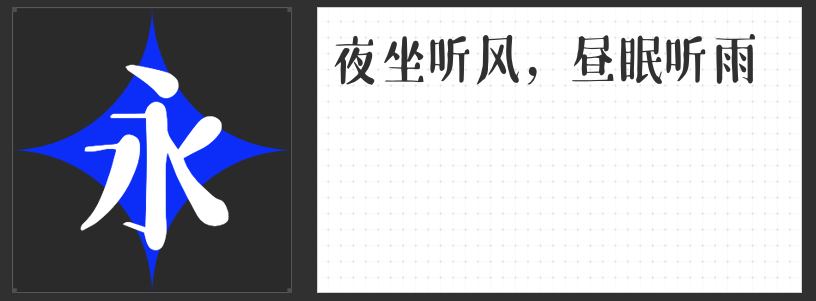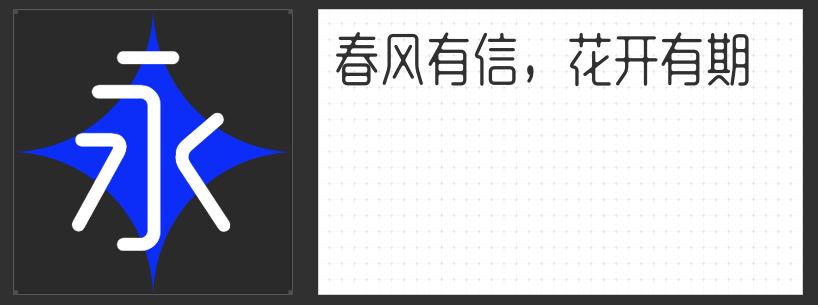
四款创意字体赋能包装设计:让视觉语言焕发独特魅力
在竞争激烈的包装设计领域,字体的选择往往成为品牌传递个性与情感的关键载体。一款兼具创意与实用性的字体,不仅能提升产品辨识度,更能通过视觉语言与消费者建立情感共鸣。以下四款非免费创意字体,以其独特的设计语言与美学表达,为包装设计注入鲜活生命力。
一、高手庆科自由宋 常规
这款以手写感为基底的宋体,突破传统宋体的刻板印象,通过圆润略瘦长的字形与适中的中宫设计,营造出灵动而不失雅致的视觉效果。横画末端的圆形装饰角与细长圆润的钩笔,赋予文字趣味性;西文符号的圆润处理更与中文形成风格统一,适用于追求文化底蕴与年轻化表达的品牌包装。
二、字恋狂风摇简 粗体
“摇晃感”是这款字体的核心标签。通过失衡的笔画比例与歪扭的线条,模拟被风吹拂的动态,传递出温暖而随性的视觉温度。其手写特质与夸张的形态处理,适合用于儿童产品、手作工艺或强调人文关怀的包装设计,以不规则的美感打破常规,激发情感共鸣。
三、励字志向黑简 中粗
圆体与黑体的融合创新,赋予这款字体独特的视觉张力。外圆角的笔画拐角设计,在保持字形稳重的同时注入灵动气息;充实的字面与稳定的结构适配屏显需求,使其成为科技产品、现代生活类包装的理想选择,兼顾专业感与亲和力。
四、高手庆科静雅体 古朴版
瘦长工整的字型与均匀的布白,构建出极简主义的视觉框架。圆角处理与小连笔设计弱化机械感,去钩的笔画转折则增添古朴韵味。这款字体适用于茶饮、文创或高端消费品包装,以“少即是多”的设计哲学传递内敛而高级的品牌气质。
四款字体各具美学基因,或灵动、或温暖、或稳重、或古朴,为包装设计提供了多元化的表达路径。选择契合品牌调性的字体,即是开启一场与消费者的视觉对话。